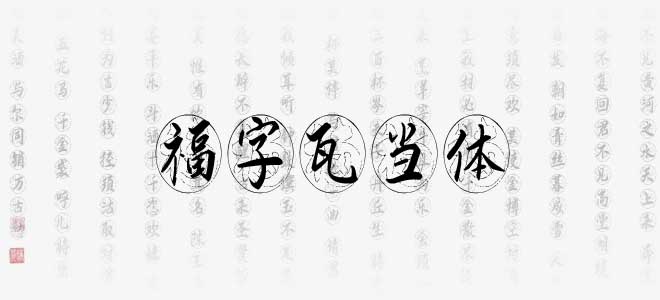
福字瓦當(dāng)體是一款非常漂亮的藝術(shù)字體,具有強(qiáng)烈的視覺沖擊力是報(bào)紙、雜志和書籍中常用字體,被用于海報(bào)、電商海報(bào)設(shè)計(jì)、店鋪設(shè)計(jì)、標(biāo)志設(shè)計(jì)、字體設(shè)計(jì)等領(lǐng)域,歡迎喜歡這款字體的朋友下載使用。
福字瓦當(dāng)體